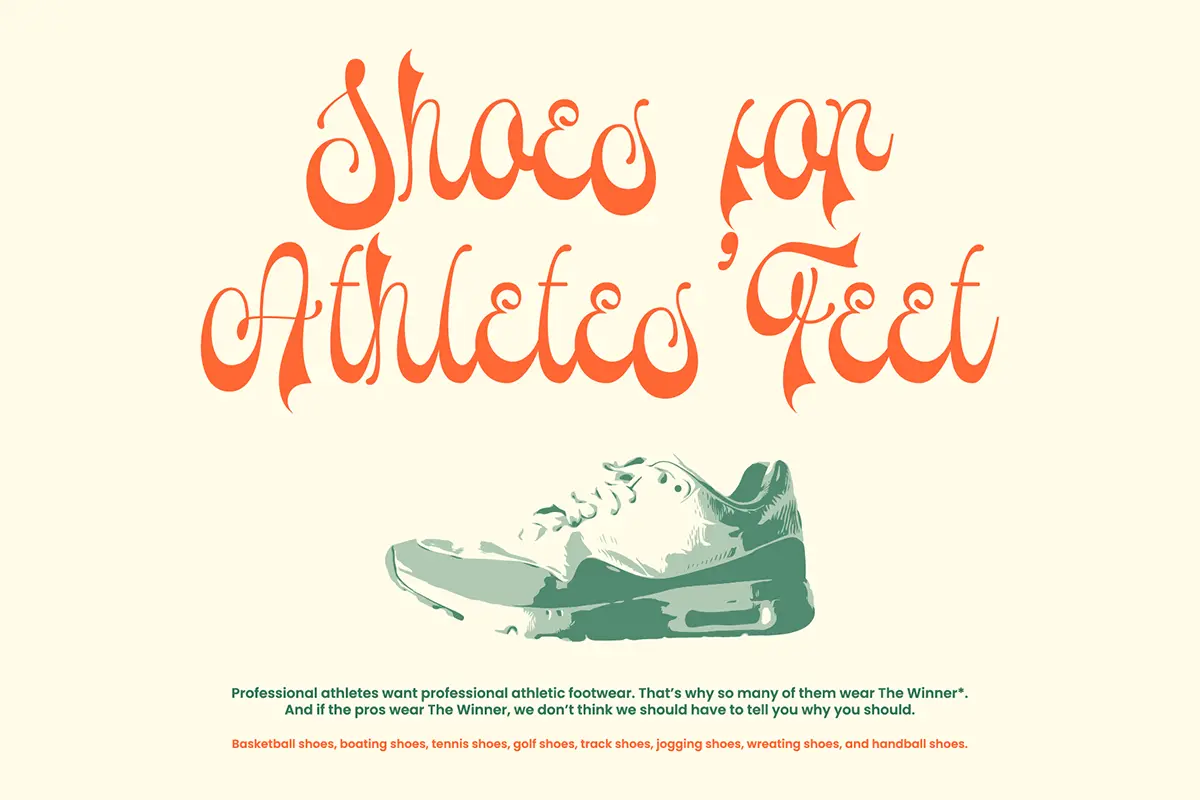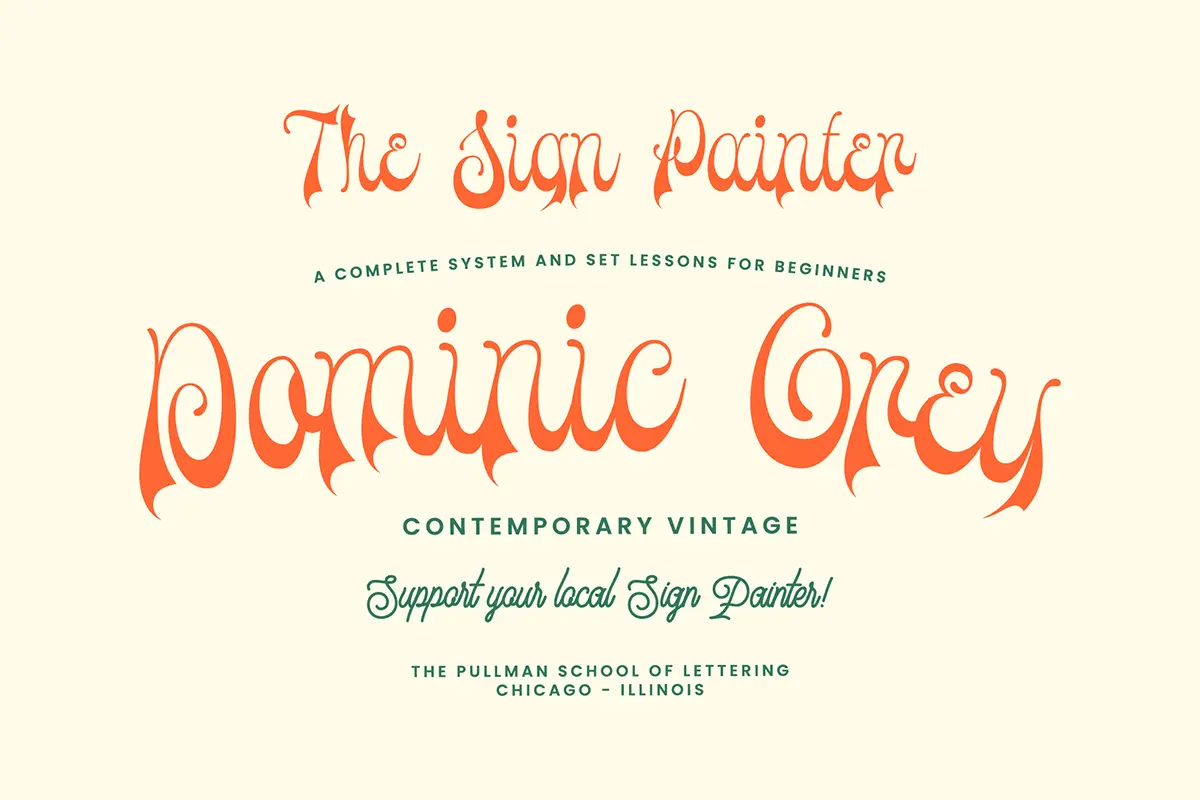
فونت دست نویس وینتیج و کلاسیک
فونت Flumerya یک فونت دست نویس وینتیج با جزئیات ظریف و زیباست که به طراحیهای شما حس شخصیسازی و اصالت میبخشه. این فونت برای پروژههایی که نیاز به ظرافت و جلوه خاص دارن عالیه و میتونه بهسرعت به انتخاب محبوبت تبدیل بشه.
⭐ ویژگیهای محصول
- فونت دستنویس با سبک وینتیج و کلاسیک
- جزئیات دقیق و طراحی منحصربهفرد
- مناسب برای پروژههای چاپی و دیجیتال
- افزودن حس شخصیسازی و ظرافت به هر طرح
🎯 موارد استفاده
- طراحی کارت دعوت عروسی
- کارتهای تشکر و تبریک
- نقلقولها و نوشتههای تزئینی
- کارتهای تبریک و مناسبتها
- لوگو و کارت ویزیت
- هر پروژهای که نیاز به لمس شخصی و خاص داشته باشد